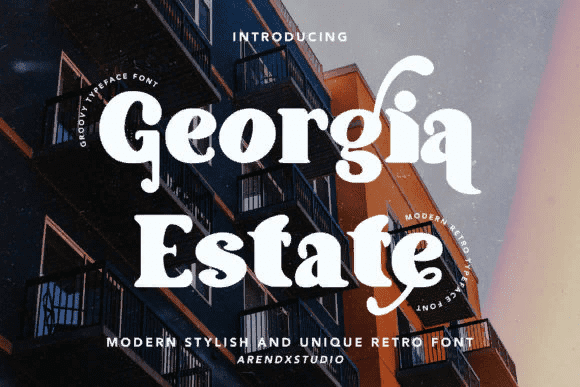
Название: Georgia Estate Font (2021)
Georgia Estate - это уникальный ретро-шрифт с засечками, с характерными символами и крутым вкусом.
Он идеально подходит для брендинговых проектов, логотипов, свадебных дизайнов, постов в СМИ, рекламы, упаковки товаров, дизайна продукции, этикеток, фотографий, водяных знаков, приглашений, канцелярских принадлежностей и многого другого.